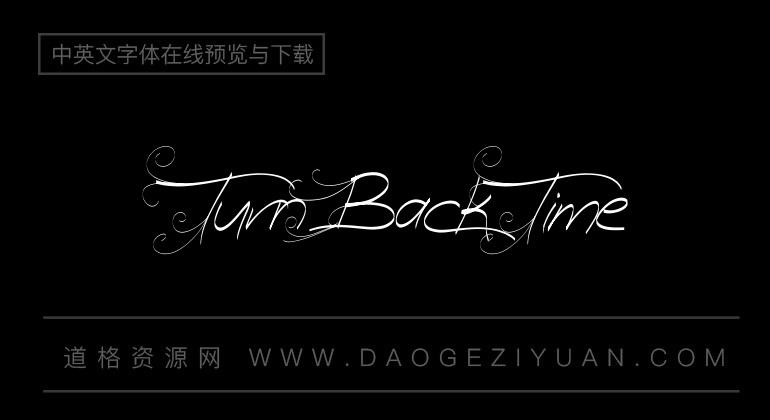
Turn Back Time 是一种简洁而又优雅的手写风格字体。其基本特点包括: 1. 字母形状流畅: Turn Back Time 字母形状流畅自然,整体上看起来非常舒适和易读。 2. 带有手写风格: Turn Back Time 字体仿佛是用笔写在纸上的,带有一定的手写感觉,具有一定的个性和温暖的情感。 3. 多样化的字形:该字体的每个字母形状都各不相同,让每个字母都显得独一无二。 4. 具有变化的字体粗细:字体的粗细不是一成不变,而是具有一定的变化,让整个字体看起来更加有层次感和立体感。 总之,Turn Back Time 字体是一种非常适合用于设计印刷品、海报、广告、包装等场合的优美字体。内容介绍
Turn Back Time是一款非常不错的手写艺术字体,具有很好的视觉感,适合于文化类的宣传设计、商业类品牌的广告和产品包装设计以及个性化文字排版等较多场景。